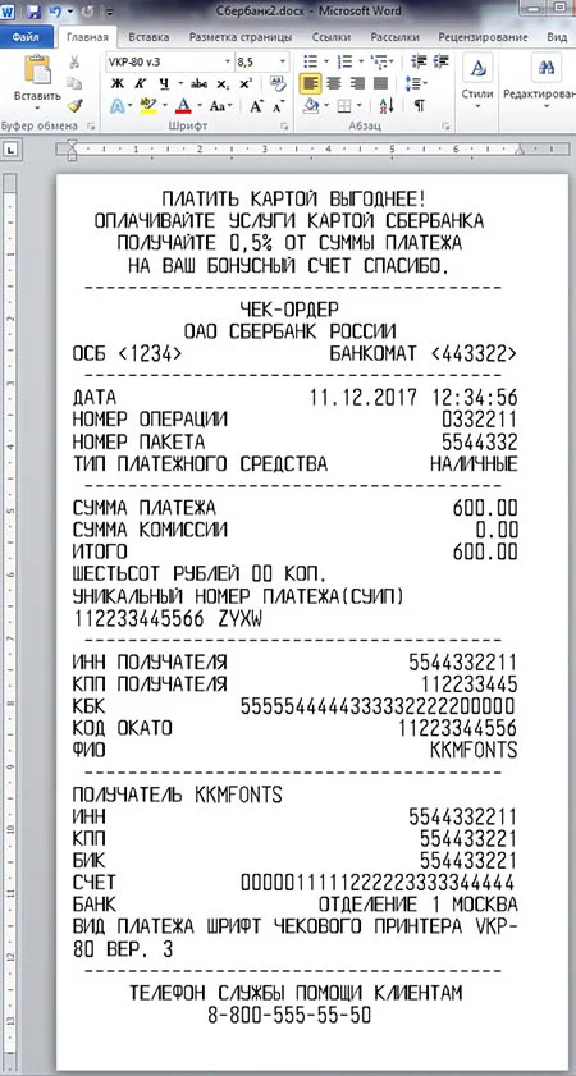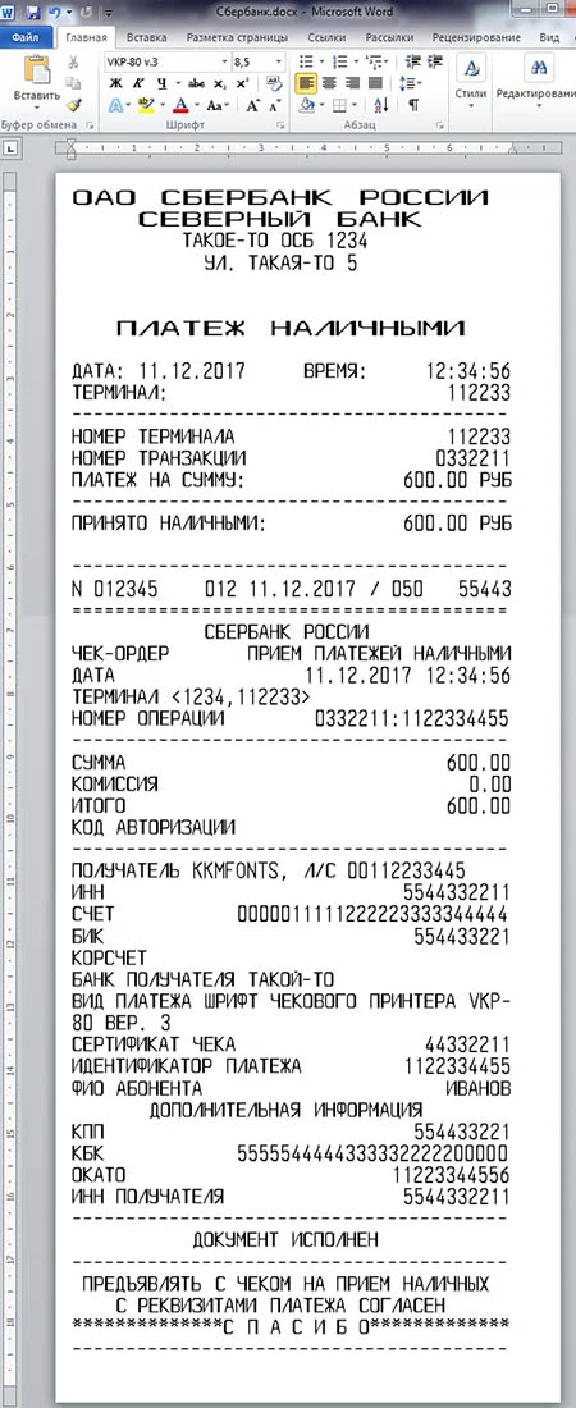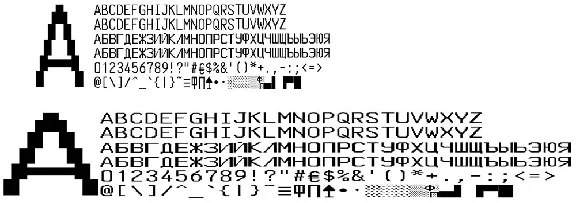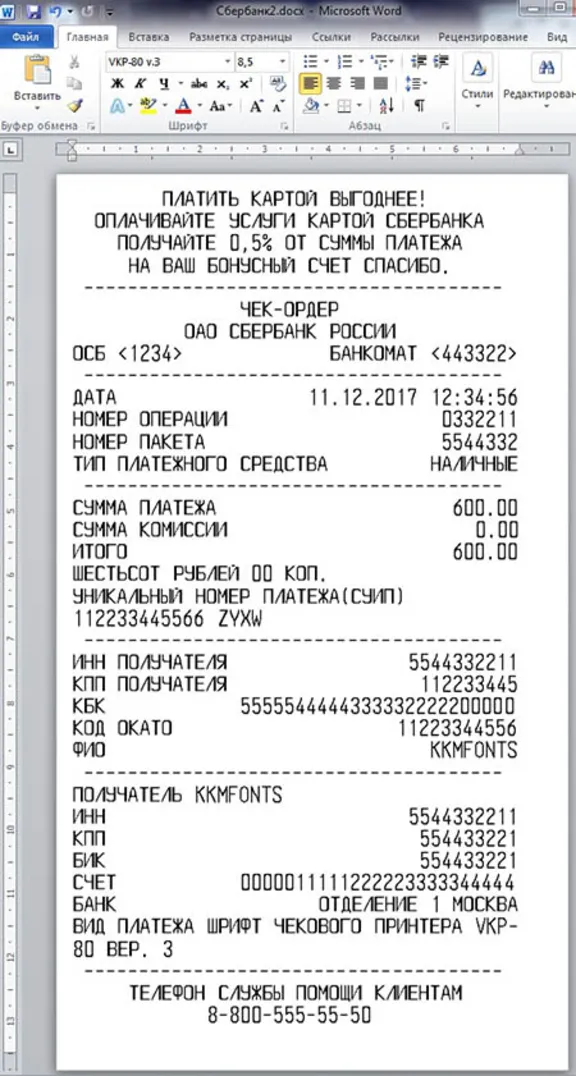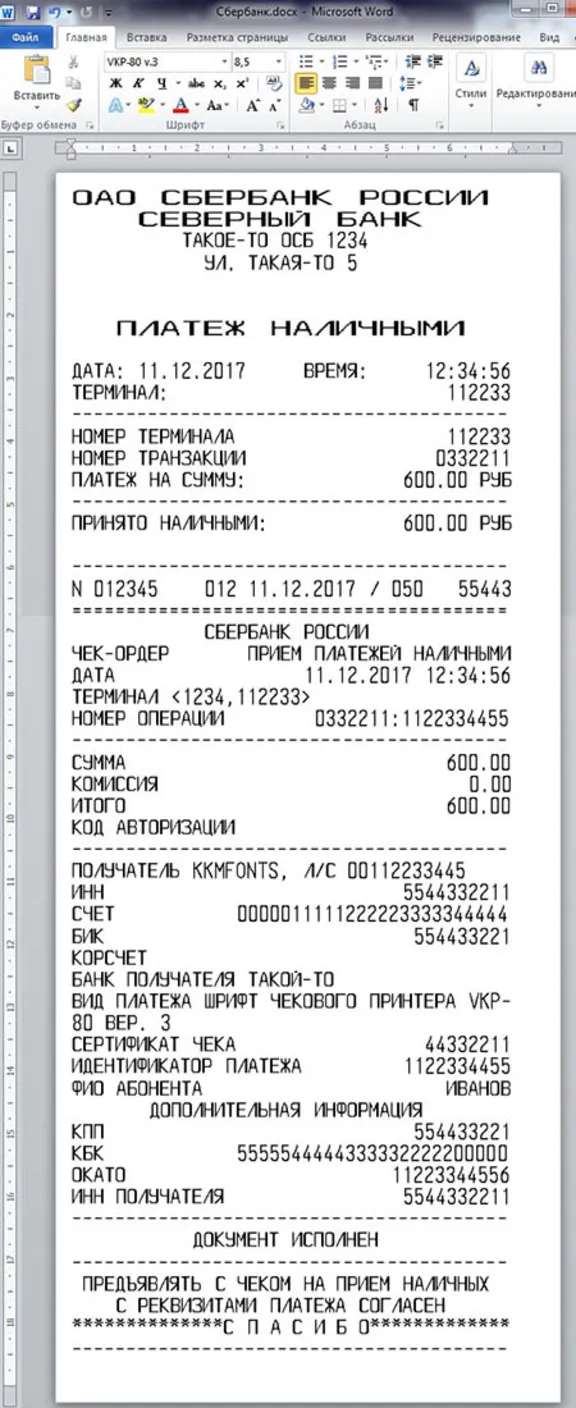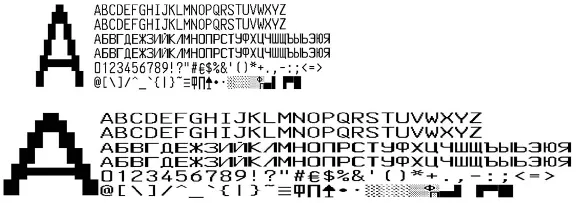
Шрифты чекового принтера VKP-80(версия 3), который устанавливается во многие терминалы оплаты, в частности СБЕРБАНК РОССИИ в формате OTF (русские и английские буквы) для использования в программе Microsoft Word. В архиве находятся нормальный и широкий шрифты в формате OTF и шаблоны чеков. Вам остается только установить шрифты в систему (обычно C:\WINDOWS\Fonts), открыть шаблон и начать редактирование.